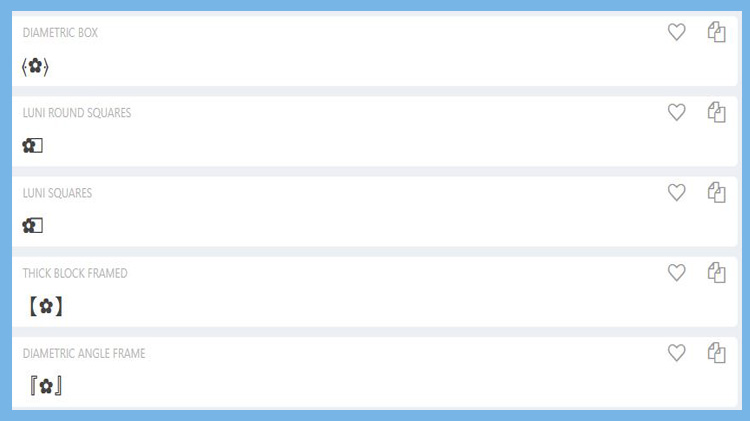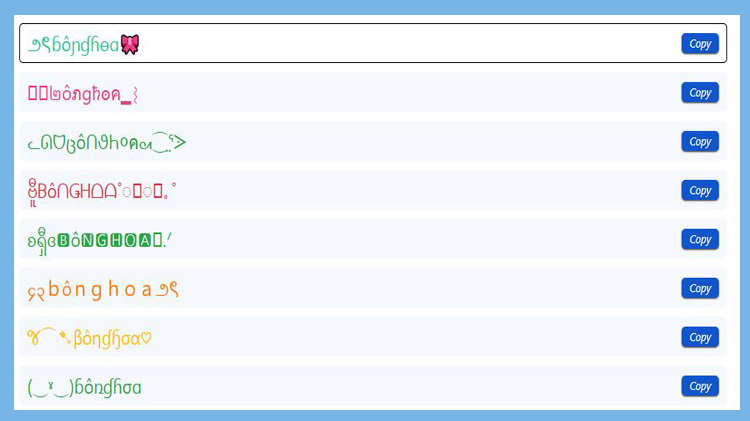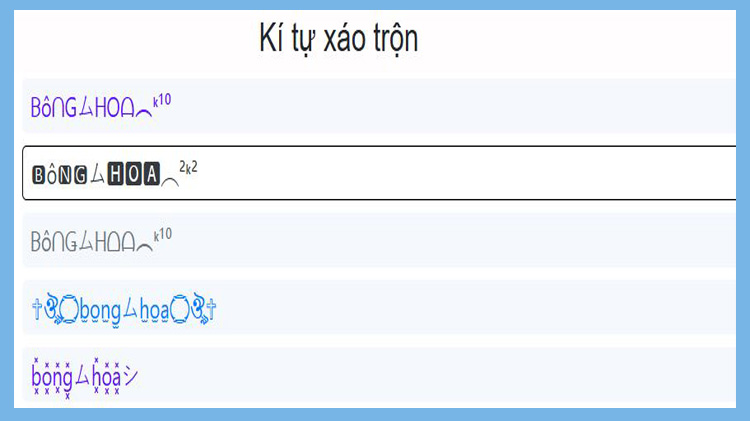
99+ Ký tự bông hoa đặc biệt, có màu sắc, đẹp và xáo trộn trên các nền tảng số
Ký tự bông hoa là những biểu tượng văn bản được thiết kế dựa trên chuẩn Unicode, mang hình dáng của những bông hoa như ✿, ❀, hay ❃. Chúng được sử dụng để trang trí văn bản, tạo điểm nhấn, hoặc mang ý nghĩa tượng trưng liên quan đến hoa lá, thiên nhiên, vẻ đẹp, sự tươi mới.
Bài viết sau của Mobifonts sẽ tổng hợp giúp bạn 4 nhóm kí tự hoa chính bao gồm: kí tự bông hoa cơ bản, có màu sắc, kí tự bông hoa chữ đẹp và hoa xáo trộn. Ngoài ra, bạn sẽ được giải đáp những thắc mắc hay gặp về các kí tự đặc biệt này.
Icon ký tự đặc biệt bông hoa thường được sử dụng hiện nay là các biểu tượng Unicode mô phỏng hình ảnh hoa lá, được sử dụng để trang trí văn bản. Theo Unicode Consortium, các ký tự này được cho phép hiển thị trên hầu hết các thiết bị và nền tảng, từ điện thoại thông minh đến máy tính.
Vì vậy sử dụng những biểu tượng hoa xinh xắn này sẽ giúp nội dung của bạn trên các nền tảng số trở nên độc đáo và cuốn hút hơn bao giờ hết!
Dưới đây là một số mẫu ký tự hoa bạn có thể sử dụng ngay:
Ký tự hoa không chỉ giới hạn trong những hình dạng cơ bản, mà còn có thể được kết hợp với màu sắc như kí tự hoa màu đỏ, xanh, vàng,... để tạo nên những hiệu ứng đẹp mắt và nổi bật. Việc sử dụng ký tự bông hoa có màu sắc không chỉ giúp tăng tính thẩm mỹ mà còn khiến nội dung của bạn trở nên thu hút hơn. Cùng chúng tôi khám phá trong nội dung sau đây.
Trong ngôn ngữ của các loài hoa, màu đỏ thường tượng trưng cho tình yêu mãnh liệt, sự tôn trọng, lòng dũng cảm và khao khát (Theo nghiên cứu của Bloom&Wild). Nên khi sử dụng kí tự đặc biệt bông hoa đỏ giúp nội dung của bạn trở nên nổi bật và thu hút hơn. Một số kí tự hoa màu đỏ được sử dụng trên các nền tảng Facebook, Instagram hay Tiktok để tăng tính thẩm mỹ như:
Nếu hoa màu đỏ tượng trưng cho sự mãnh liệt thì bông hoa màu xanh tượng trưng cho sự tươi mới, hy vọng và bình yên (Theo Bloom&Wild). Nếu bạn muốn làm nổi bật nội dung của mình, hãy thử ngay các ký tự đặc biệt bông hoa xanh độc đáo dưới đây. Bạn có thể sử dụng những ký tự hoa xanh sau:
Theo các nghiên cứu về tâm lý học màu sắc loài hoa của Bloom&Wild, màu vàng tượng trưng cho sự rực rỡ, may mắn và tiền tài. Cho nên khi sử dụng biểu tượng kí tự đặc biệt bông hoa 5 cánh màu vàng giúp nội dung của bạn thêm nổi bật và thu hút hơn trên mọi nền tảng. Một số ký tự hoa 5 cánh bạn có thể tham khảo là:
Bên cạnh những kí tự hoa với màu sắc sặc sỡ thì ký tự đặc biệt bông hoa chữ đẹp sẽ giúp bạn biến những dòng chữ đơn điệu thành tác phẩm nghệ thuật, mang phong cách riêng đầy sáng tạo. Một vài ví dụ về các ký tự hoa kết hợp với chữ đẹp bạn có thể tham khảo như
Ký tự hoa xáo trộn là sự sáng tạo đầy ngẫu hứng giữa các kí tự đặc biệt, chữ và số, giúp nội dung của bạn trở nên độc đáo và cuốn hút hơn. Hãy thử kết hợp các kí tự đặc biệt hoa để tạo nên những hiệu ứng mới lạ và ấn tượng. Tham khảo một số sự kết hợp gợi ý sau của Mobifonts như:
Ký tự hoa xáo trộn này giúp làm nổi bật thông điệp của bạn, đồng thời tạo ấn tượng mạnh mẽ trong mắt người xem.
Các câu hỏi thường gặp về ký tự bông hoa hay thắc mắc sẽ được giải đáp ngay dưới đây nhé:
Hoàn toàn có thể tạo các ký tự đặc biệt bông hoa theo ý muốn!
Bước 3: Chọn phong cách yêu thích, nhấn "Sao chép", và dán ngay vào bất kỳ nền tảng nào bạn muốn!
Thử ngay để làm nổi bật nội dung của bạn với những kí tự bông hoa đầy sáng tạo và độc đáo!
Icon bông hoa có thể sử dụng trên hầu hết các nền tảng và các ứng dụng nhắn tin trên mọi thiết bị hoặc hệ điều hành. Tuy nhiên để đảm bảo chúng được hiển thị đúng như mong muốn, bạn nên kiểm tra các quy định của phía nền tảng số.
Có! Bạn có thể kết hợp icon bông hoa với nhiều kí tự đặc biệt khác và các chữ cách điệu để tạo nên những đoạn văn bản hoặc tên hiển thị độc đáo. Điều này giúp bạn cá nhân hóa nội dung và làm cho bài đăng trên mạng xã hội trở nên thu hút hơn.
Ký tự bông hoa không chỉ là những hình vẽ dễ thương mà còn mang trong mình nhiều ý nghĩa sâu sắc. Hãy thử ngay trên Mobifonts các ký tự đặc biệt bông hoa 5 cánh, hoa màu sắc, và những biến thể sáng tạo khác để làm mới nội dung của mình!